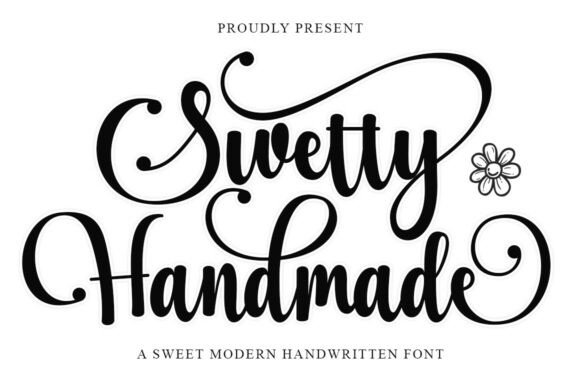
Sweetty Handmade
Sweetty Handmade์™€ ๊ฐ™์€ ๊ณ ํ’ˆ์งˆ ์ž์‚ฐ์„ ์ฐพ๊ณ  ์žˆ๋‹ค๋ฉด ์ด ํ”„๋ฆฌ๋ฏธ์—„ ํŒจํ‚ค์ง€๋Š” ์ฐฝ์˜์ ์ธ ํ”„๋กœ์ ํŠธ๋ฅผ ์œ„ํ•œ ํ™˜์ƒ์ ์ธ ์„ ํƒ์ž…๋‹ˆ๋‹ค.
POD(์ฃผ๋ฌธํ˜• ์ธ์‡„) ์ œํ’ˆ, ๊ฒฐํ˜ผ์‹ ์ดˆ๋Œ€์žฅ ๋˜๋Š” ์†Œ์…œ ๋ฏธ๋””์–ด ๊ทธ๋ž˜ํ”ฝ์„ ๋งŒ๋“ค ๋•Œ Sweetty Handmade๋Š” ์ด์ƒ์ ์ธ ์„ ํƒ์ž…๋‹ˆ๋‹ค.